免费可商用手写字体三连发!
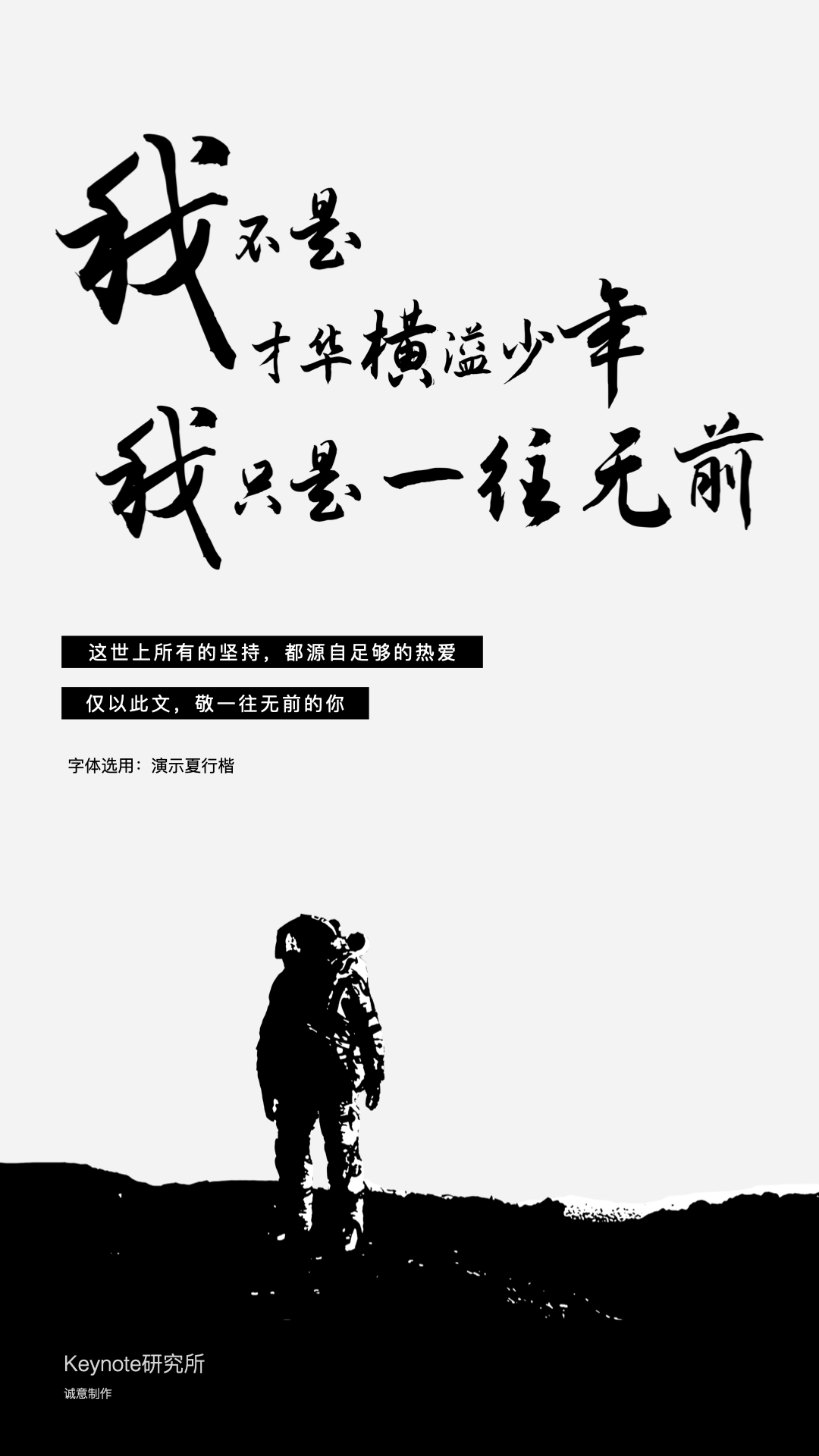
设计,重要的是,
如何解决用户所面临的当前问题
两年前,为了解决在 Keynote 中文字不能倾斜的问题,我做了一次大胆的尝试:自己动手改造出一款 Keynote 可用的倾斜字,让幻灯片设计师可以在Keynote中一键倾斜文字。于是基于对谷歌开源字体「思源黑体」的倾斜处理,便有了 — 演示斜黑体。但很多人说,这款字应该叫做 演示斜杠体,因为是它,让关于我的故事不再是只有PPT,又加上了一道斜杠——字体。
优秀幻灯片,
集巧妙的逻辑编排与可视化图形语言于一身,
使原本枯燥的内容,
变得更加易懂且利于表述,
甚至可以引起大范围传播
发展到今天,PPT 已经不局限于“大字报工具”,它更像是一个多媒体容器,集合了图形语言、图标元素、风格字体、图片视频、3D模型·········从“实用为先”到兼顾“策略与颜值”的双重美学。甚至,它已为很多人创造了就业机会,当然也包括我。
商业幻灯片委托,
不仅要帮客户完成项目,
更要帮他们规避风险
事实上,大多数风险行为与字体和图片侵权有关,这源自仍有很多企业对于版权意识的淡薄,以及少有能力去支付高昂的授权费。虽然字体和图片被称作是设计师的“油盐酱醋”,但实际情况却是:好字体不敢用,好图片没钱用。所以,我希望为它做一些更有价值的事情。于是便有了《演示新手书》与《演示镇魂行楷》两款字体,皆为幻灯片而生的实用字体!当然,也要特别感谢 P 圈的众多朋友,让这两款现在看来依旧很不成熟的字,出现在了越来越多的重要的演示场合,让它们源于演示,也不止于演示。
这两年,
关于字体的世界,
在悄然发生着变化
越来越多的免费商用字体、平价字体,如雨后春笋般一个接一个地发布出来。有标准字,有手写字,有美术字 ······
演示新手书与演示镇魂行楷,
这两款字体于我而言,意义重大
但谩骂声也从未停止
熟话说:
武无高低,唯用武之人有强弱之别。
茶无贵贱,唯品茶之人一杯以入心。
我左右不了任何人,我的态度是:
如果你觉得好看,就用。一款字体无人可用将会是它最大的悲哀,能把字体用起来就是对作者最大的帮助。
如果你觉得不好看,就别用,我并不欠任何人。
今年3月,
我发布了两款免费可商用手写字体
演示佛系体 和 演示悠然小楷 分别来自纪国才老先生和孟祥媛同学的手写字稿。得益于在做字技术上的突破,从字稿到字体的封包效率几乎越来越快,已经可以实现3天内结束字体封包。今天我将再次发布三款免费可商用字体,全部为半自动流程制作,当然我也已经做好了被某些人骂的准备,似乎一切手写字体都天生具备这种基因,所以,请让你们的狂风暴雨来的更猛烈一些吧!这三款字分别为:演示春风楷、演示夏行楷、演示秋鸿楷。
演示春风楷
字稿作者:徐占海
1983年入伍,军人出身丨辽宁人丨每日笔耕不辍
字体制作:人生哥(和他的半自动电脑)
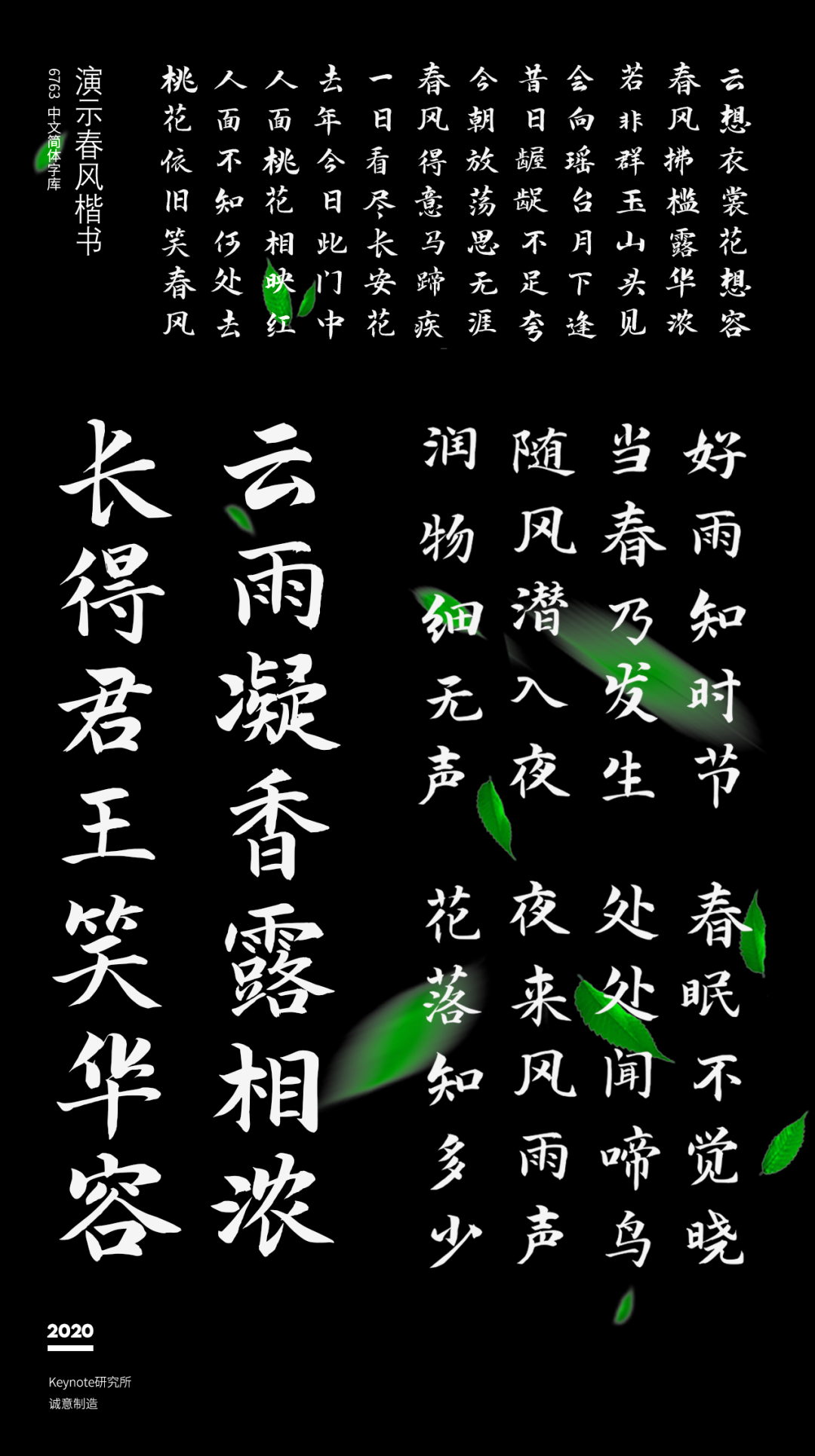
演示夏行楷
字稿作者:刘锡栋
中国漓江书画艺术家协会理事丨北京中国书画研究院研究员丨中国民族硬笔书法家协会会员丨中国楹联学会会员丨黑龙江楹联家协会会员丨高级政工师,已退休
字体制作:人生哥(和他的半自动电脑)
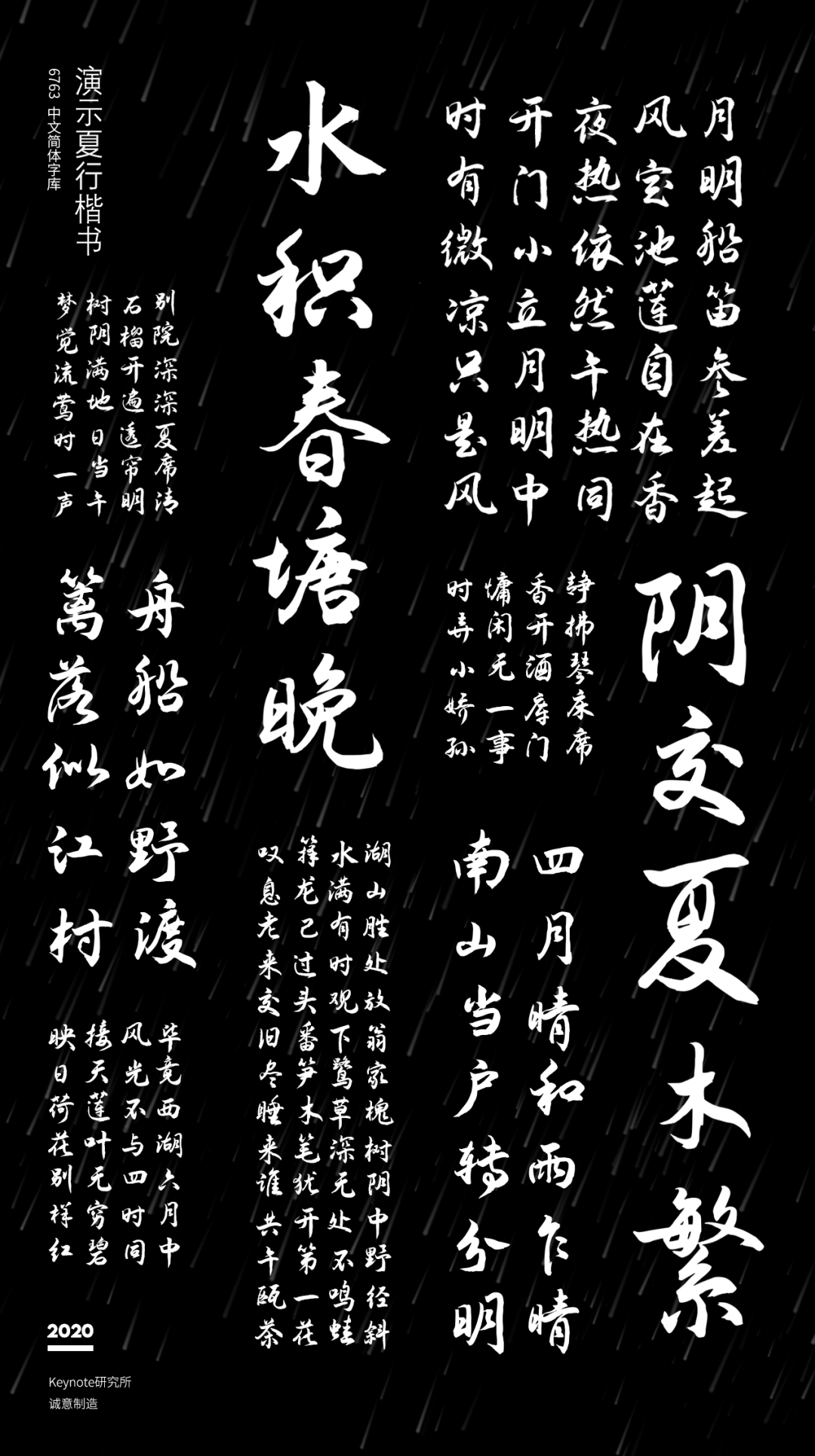
演示秋鸿楷
字稿作者:叶运鹏
高中教师丨辽宁人丨98年加入农民书画家协会
字体制作:人生哥(和他的半自动电脑)
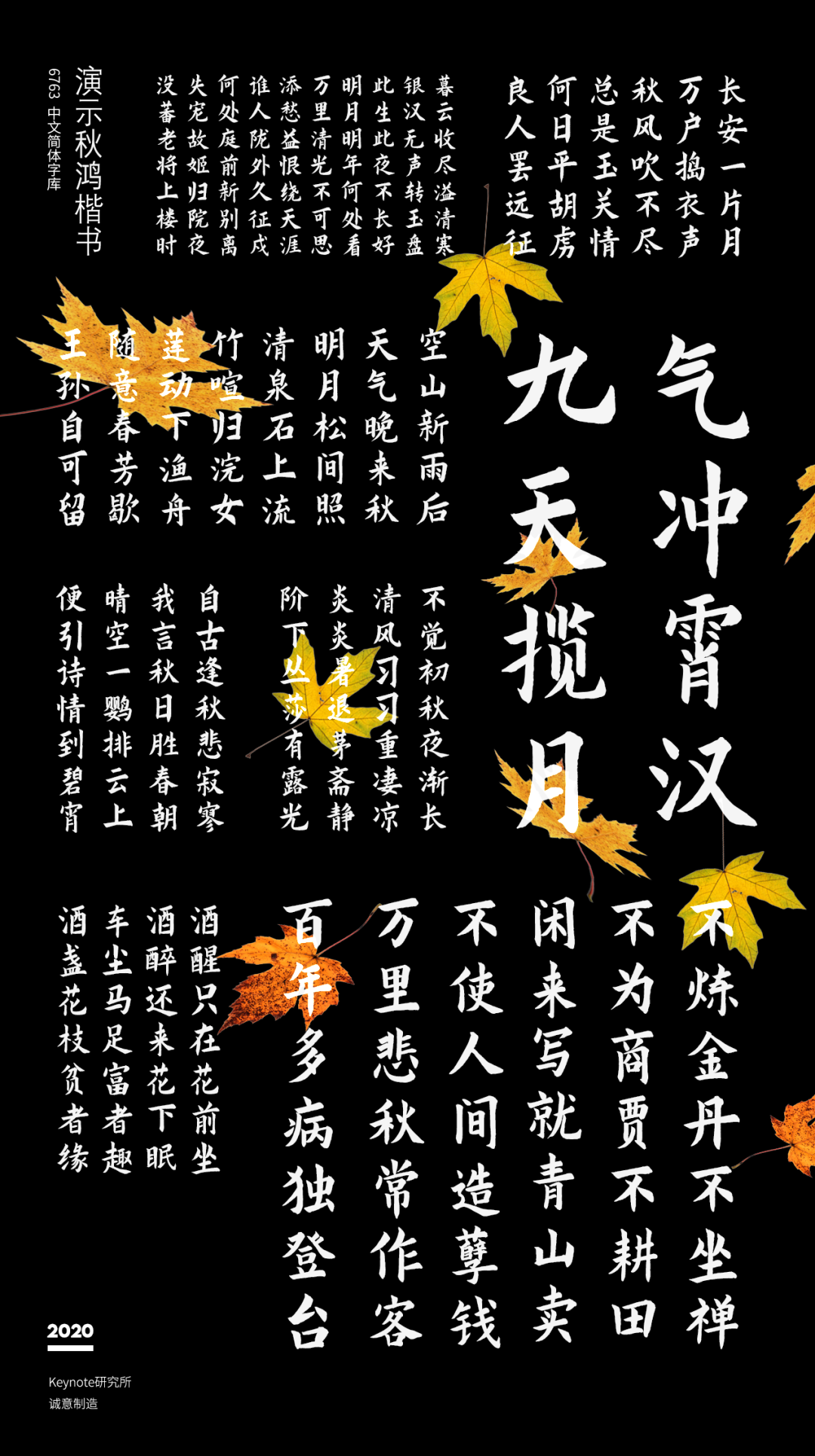
都是普通人,愿都能尽一份力。另外,我还邀请了一些 P 圈的设计师好友共同来写字,分别是:向天歌—冯注龙,前Ableslide设计师—阿正,秋叶PPT—百合,邹氏PPT—邹叔等,即将与你们见面。如果你写得一手好字,我也愿意帮你制作成字库。